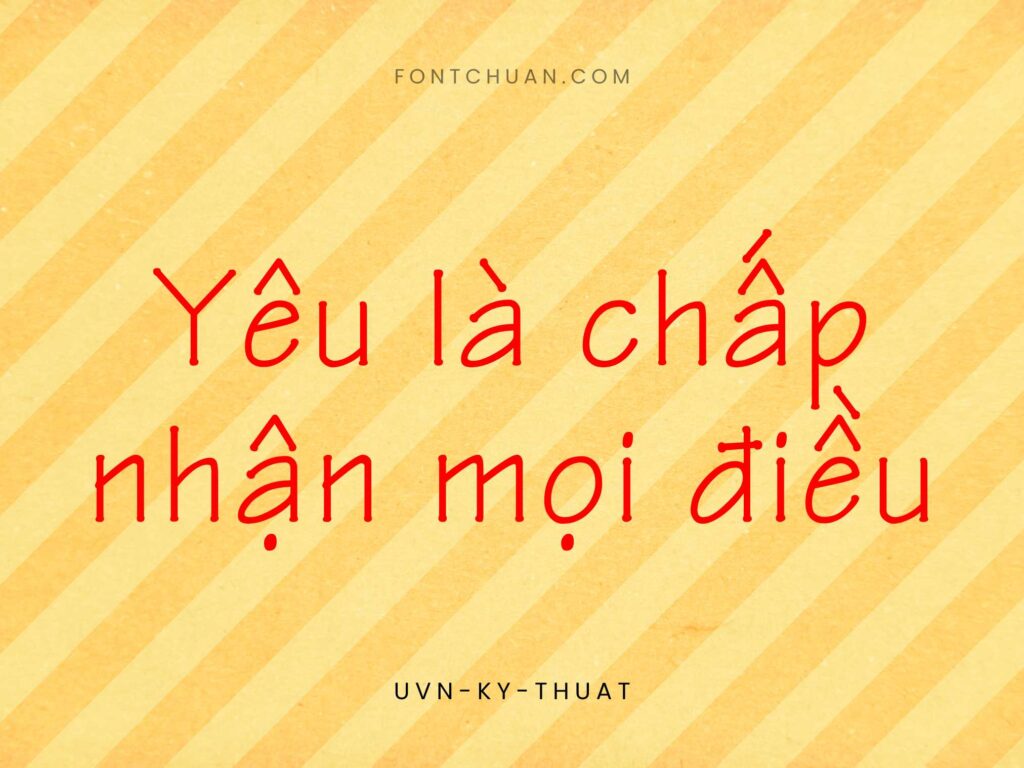
Font UVN Ky Thuat Việt Hóa
UVN Kỹ Thuật là một phông chữ sans-serif được thiết kế bởi Tom Trương vào năm 2001. Phông chữ này có các đường nét đơn giản, rõ ràng và hiện đại, tạo nên sự chuyên nghiệp và dễ đọc trong các thiết kế kỹ thuật và công nghiệp. Với đặc tính gọn gàng và cân đối, UVN Kỹ Thuật còn có thể được xếp vào nhóm Font Monospace nhờ khả năng hiển thị chữ đều đặn, phù hợp cho các tài liệu cần độ chính xác cao. Ngoài ra, đây cũng là một Font chữ giáo dục hữu ích, thường được áp dụng trong sách giáo khoa, tài liệu giảng dạy và các sản phẩm học tập nhờ tính dễ đọc và tính ứng dụng rộng rãi. UVN Kỹ Thuật hỗ trợ đầy đủ các ký tự tiếng Việt, giúp người dùng dễ dàng sử dụng trong các dự án liên quan đến ngôn ngữ Việt Nam.
Với thiết kế đơn giản và rõ ràng, UVN Kỹ Thuật phù hợp cho các ứng dụng như tài liệu kỹ thuật, bản vẽ, báo cáo, thiết kế logo và các ấn phẩm cần sự chính xác và chuyên nghiệp. Trong lĩnh vực sự kiện, phông chữ này có thể được sử dụng trong các hội thảo, triển lãm công nghệ và các sự kiện chuyên ngành. Ngoài ra, UVN Kỹ Thuật cũng thích hợp cho các ngành nghề như kỹ thuật, công nghệ, sản xuất và giáo dục.